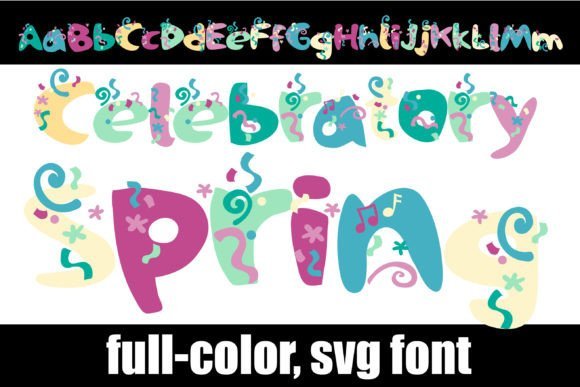
Celebratory Spring Font
Celebratory Spring Font – الخط المثالي لتصاميم الربيع المبهجة!
احتفل بجمال الربيع مع Celebratory Spring Font، الخط العصري والأنيق الذي يجمع بين الأناقة والمرح. يتميز بتصميمه الجذاب وانحناءاته الناعمة التي تضيف لمسة احتفالية لأي مشروع تصميمي.
✨ مميزات الخط:
✔ تصميم أنيق ومبهج يناسب أجواء الربيع والاحتفالات
✔ مثالي للتصميمات الدعائية، الدعوات، الشعارات، البطاقات، وغيرها
أضف لمسة من البهجة والجمال إلى تصاميمك مع Celebratory Spring Font! ????????